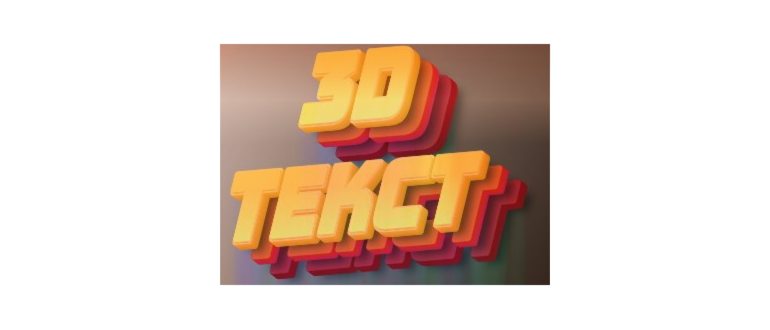
Клавиатура является основным инструментом работы на компьютере, и правильный выбор шрифта важен для создания красивого и удобного текста. Некоторые люди страдают от недостатка внимания к деталям и печатают безразлично. Однако, существуют методы, которые помогут вам создать красивый шрифт даже на обычной клавиатуре.
Первым способом является использование жирного шрифта. Жирный шрифт делает текст более выразительным и увеличивает его читаемость. Для создания жирного шрифта на клавиатуре, используйте комбинацию клавиш «Ctrl» + «B».
Второй способ — это курсив. Курсивный шрифт придает тексту эффект наклона и делает его мягче. Для создания курсивного шрифта на клавиатуре, используйте комбинацию клавиш «Ctrl» + «I».
Третий способ — это подчеркивание. Подчеркивание помогает выделить важные части текста и делает его более ярким. Для создания подчеркнутого шрифта на клавиатуре, используйте комбинацию клавиш «Ctrl» + «U».
Четвертым способом является выделение по контуру. Выделение по контуру добавляет тексту контур и делает его более заметным. Для создания выделения по контуру на клавиатуре, используйте комбинацию клавиш «Ctrl» + «Shift» + «O».
Пятый способ — это использование больших букв. Большие буквы привлекают внимание и делают текст более удобочитаемым. Для создания больших букв на клавиатуре, удерживайте клавишу «Caps Lock» включенной.
Шестой способ — это использование моноширинного шрифта. Моноширинный шрифт имеет одинаковую ширину для всех символов и делает текст более аккуратным и ровным. Для выбора моноширинного шрифта на клавиатуре, используйте комбинацию клавиш «Ctrl» + «Shift» + «M».
Седьмым способом является изменение размера шрифта. Увеличение или уменьшение размера шрифта может сделать текст более читаемым или добавить ему стильности. Для изменения размера шрифта на клавиатуре, используйте комбинацию клавиш «Ctrl» + «+» для увеличения или «Ctrl» + «-» для уменьшения.
7 способов создать красивый шрифт на клавиатуре
Создание красивого шрифта на клавиатуре может быть легким и интересным заданием. Ниже приведены семь способов, которые помогут вам создать стильный и оригинальный шрифт, используя только клавиатуру:
- Использование символов и специальных знаков. Некоторые клавиатурные символы могут быть использованы для создания интересных эффектов. Например, вы можете использовать символы, такие как «*»,»_»,»=» и другие, чтобы добавить украшение к вашему шрифту.
- Изменение размера шрифта. Вы можете изменить размер шрифта, используя клавишу «Ctrl» и «+»/»-» для увеличения или уменьшения размера шрифта соответственно. Это может помочь вам создать различные варианты шрифта с разными размерами текста.
- Использование различных шрифтов и стилей. Существует большое разнообразие шрифтов и стилей, доступных на клавиатуре. Вы можете использовать разные комбинации шрифтов, таких как «Arial», «Times New Roman», «Courier New» и других, чтобы создать уникальный шрифт.
- Применение эффектов форматирования. Вы можете использовать различные эффекты форматирования, такие как жирный, курсив, подчеркивание, чтобы выделить ваш текст и сделать его более привлекательным.
- Использование цветовых схем. Вы можете изменить цвет текста, используя комбинацию клавиш «Ctrl» и «K» для открытия палитры цветов. Выберите цвет, который наиболее подходит для вашего шрифта, чтобы сделать его более ярким и привлекательным.
- Изменение выравнивания и отступов. Вы можете изменить выравнивание и отступы вашего текста, чтобы создать уникальный и эстетически приятный шрифт.
- Использование таблицы. Вы можете использовать таблицу для создания структурированного и организованного шрифта. Разделите ваш текст на ячейки таблицы и установите различные стили для каждой ячейки.
Использование этих семи способов поможет вам создать красивый и стильный шрифт на клавиатуре. Экспериментируйте с разными комбинациями и стилями, чтобы найти наиболее подходящий для вас результат.
Используйте специальные символы и символы Unicode
Для создания красивого шрифта на клавиатуре можно использовать специальные символы и символы Unicode. Они помогут разнообразить текст, добавить оригинальность и привлечь внимание читателей.
1. Специальные символы:
- • Создайте ненумерованный список, добавив символ «мишень» – • – перед элементом списка.
- ◦ Отметьте пункты нумерованного списка с помощью символа «белый круг с точкой» – ◦.
2. Символы Unicode:
Используйте символы Unicode для добавления различных символов и декоративных элементов в свой текст. Ниже приведены примеры некоторых символов:
- ➡ Добавьте стрелку вправо, используя символ Unicode – ➡.
- ✔ Вставьте символ проверки, обратившись к коду Unicode – ✔.
- ❤ Для символа сердца воспользуйтесь кодом Unicode – ❤.
3. Символы для украшения текста:
Воспользуйтесь символами для украшения текста и добавления различных эффектов:
- ???? Для использования символа шрифта курсива используйте символ Unicode – ????.
- ???? Примените шрифт фракции к тексту, используя символ Unicode – ????.
| Символ | Описание |
|---|---|
| © | Символ «копирайт» |
| № | Символ «номер» |
| ≠ | Символ «не равно» |
Используйте эти специальные символы и символы Unicode в своем тексте, чтобы сделать его более интересным и привлекательным для чтения. Это отличный способ добавить оригинальность и индивидуальность в ваши сообщения и статьи.
Экспериментируйте с размером, шрифтом и выравниванием текста
Один из способов создать красивый шрифт на клавиатуре — это экспериментировать с размером, шрифтом и выравниванием текста. Варьируя эти параметры, вы можете создать уникальное оформление текста, которое подчеркнет его значение и привлечет внимание читателя.
Сначала рассмотрим размер шрифта. Вы можете выбрать мелкий размер шрифта для подзаголовков или небольших абзацев, чтобы создать более компактный вид. Более крупный шрифт может быть использован для заголовков или основного текста, чтобы сделать его более заметным и удобочитаемым.
Далее, выберите подходящий шрифт. Веб-браузеры предлагают множество стандартных шрифтов, но вы также можете использовать веб-шрифты или загрузить свой шрифт, если вам нужно что-то особенное. Помните, что шрифт должен быть четким и легко читаемым, даже при маленьком размере.
Не забудьте также использовать выравнивание текста, чтобы придать ему логическую структуру и сделать его более привлекательным для взгляда. Вы можете выровнять текст по левому, правому или центральному краю страницы, в зависимости от вашего предпочтения и дизайна страницы.
Использование разнообразных элементов форматирования текста таких как жирный () или курсив () может также сделать ваш текст более выразительным и захватывающим для читателя.
В заключение, экспериментируйте с размером, шрифтом и выравниванием текста на клавиатуре, чтобы создать красивый и привлекательный текст. Не бойтесь пробовать разные сочетания и находить свой уникальный стиль!
Используйте эффекты и стилизацию текста
Возможности стилизации текста на клавиатуре не ограничиваются обычным выбором шрифта. Вы можете добавить эффекты и стилизацию, чтобы сделать текст более выразительным и привлекательным.
Одним из основных способов стилизации текста является использование тегов и . Тег делает текст жирным, а тег — курсивным.
Также вы можете использовать теги
- ,
- для создания маркированных и нумерованных списков. Пример использования:
- Первый элемент списка
- Второй элемент списка
- Третий элемент списка
- Первый элемент нумерованного списка
- Второй элемент нумерованного списка
- Третий элемент нумерованного списка
Клавиатура также позволяет создавать таблицы с помощью тега
. Пример:
Заголовок 1 Заголовок 2 Заголовок 3 Ячейка 1 Ячейка 2 Ячейка 3 Ячейка 4 Ячейка 5 Ячейка 6 Используя эффекты и стилизацию текста на клавиатуре, вы можете создать красивые заголовки, акцентировать важные моменты и организовать информацию в таблицы и списки для более удобного чтения.
Используйте программы и онлайн-утилиты для создания собственных шрифтов
Когда стандартные шрифты уже надоели, можно создать свой собственный шрифт, который будет уникальным и отражать вашу индивидуальность. Сегодня существует множество программ и онлайн-утилит, которые помогут вам в этом деле. Вот несколько популярных вариантов:
- FontForge – это бесплатная и открытая программа, которая позволяет создавать и редактировать шрифты. Она поддерживает множество форматов, включая TrueType и OpenType, и предоставляет широкий набор инструментов для настройки каждого символа.
- Glyphs – это профессиональная программа для создания шрифтов, которая позволяет работать с множеством символов одновременно и автоматизировать процесс создания шрифта. Она платная, но предоставляет много возможностей для создания высококачественных шрифтов.
- FontStruct – это онлайн-утилита, которая позволяет создавать шрифты, используя графический интерфейс. Вам достаточно выбрать и настроить геометрические формы символов, чтобы создать свой уникальный шрифт.
- Calligraphr – это онлайн-утилита, которая помогает создавать шрифты на основе вашего почерка. Просто запишите буквы и цифры на бумаге, отсканируйте их и загрузите в Calligraphr. Затем вам нужно будет настроить каждый символ и сохранить готовый шрифт.
Не важно, какую программу или утилиту вы выберете, важно провести достаточное количество времени, чтобы создать шрифт, который полностью удовлетворяет вашим требованиям и ожиданиям. Выберите подходящий инструмент и начните создавать свой уникальный шрифт уже сегодня!
ПРОФИ отвечают на вопросы онлайн
Как создать красивый шрифт на клавиатуре?Существует несколько способов создания красивого шрифта на клавиатуре. Один из них — использование специальных символов и символов юникода. Также вы можете использовать различные эффекты форматирования, такие как жирный, курсив, подчеркнутый и зачеркнутый текст. Кроме того, стоит обратить внимание на размер и цвет шрифта, чтобы он соответствовал дизайну вашего текста или документа.Что такое символы юникода?Символы юникода — это специальные символы, которые не входят в обычный набор символов на клавиатуре. Они представляют собой стрелки, звездочки, сердечки и другие украшения, которые можно использовать для создания красивого шрифта. Чтобы использовать символы юникода, вам нужно знать их коды и ввести их с помощью клавиш комбинаций или специальных программ.Какие эффекты форматирования можно использовать для создания красивого шрифта?Для создания красивого шрифта вы можете использовать различные эффекты форматирования, такие как жирный, курсив, подчеркнутый и зачеркнутый текст. Каждый из этих эффектов придает вашему тексту особую эстетическую привлекательность. Они могут быть использованы как самостоятельно, так и в комбинации друг с другом для создания уникальных визуальных эффектов.Как выбрать правильный размер и цвет шрифта для создания красивого текста?Выбор размера и цвета шрифта зависит от ваших предпочтений и требований дизайна. Лучше выбрать размер шрифта, который является удобным для чтения и соответствует общей композиции текста. Цвет шрифта должен быть хорошо читаемым на фоне, на котором он будет использоваться. Идеальное сочетание размера и цвета шрифта создаст красивый и гармоничный текст.С помощью сторонних программ
- Установите программу с помощью «Плей Маркета». Запустите её, откройте вкладку «Мой». Щёлкните по настройкам.
Посмотрите, как выглядит новый стиль шрифта в системе и приложениях
Если в настройках устройства вы не нашли штатного инструмента для смены шрифта, вам нужно скачать и установить стороннюю утилиту с «Плей Маркета», например, iFont. Перед этим вам нужно установить в телефоне права «Рут», то есть получить права администратора смартфона, с которыми можно менять тонкие параметры системы. Для этого можно взять программу KingoRoot.
Опубликовано в Интересное
Как Сделать Красивый Шрифт на КлавиатуреСвободно переключаться на другие предустановленные в систему шрифты могут владельцы телефонов Samsung. Для этого:10 комментариевЮзабельна для меня только fonttextup.com полноценный конструктор надписей можно добавлять всякие эффекты шрифтаму меня в закладках 3 сайта — где я могу сгенерировать + скопировать и вставить сразу хуть на YouTube или еще куда. без всяких HTML, и всяких ⛎.
При использовании материалов с sdelaicomp.ru обязательным условием является использование ссылки на сайт
Мы более релевантной рекламы
Пользуясь сайтом, Вы автоматически принимаете «Пользовательское соглашение», а также правила передачи и обработки персональных данных, описанные в «Политике конфиденциальности»
Это абсолютно нормально для некоторых символов появляться в виде квадратов.
Хотите добавить свои собственные творения или не можете что-то найти? Отправьте нам сообщение! KонтактWhatsApp
В приложении WhatsApp очень ограниченные настройки шрифтов. Выбрать начертание, к сожалению, нельзя, доступно лишь изменение размера.
Особенность мессенджера WhatsApp в том, что вы можете форматировать текст в диалогах.
В Ватсапп доступно четыре стиля написания, которые используют для выделения важных мест в сообщении или повышения точности передачи информации.
- Чтобы написать текст жирным шрифтом, оберните его знаком * с двух сторон. Например, *CompConfig*. После отправки сообщения текст между звёздочками станет жирным.
- Для добавления курсива оберните слово или фразу нижним подчёркиванием _. Например, _Читайте нас_. Важно, чтобы перед первым нижним подчёркиваением и после второго был пробел. Форматирование применяется после отправки сообщения.
- Для создания зачёркнутого текста используйте знак тильды ~. Принцип аналогичный — оборачиваете слово или фразу с двух сторон и отправляете сообщение.
Ещё одна возможность — добавление в чат моноширинного начертания, которым часто пользуются разработчики. В WhatsApp доступен шрифт FixedSys. Чтобы применить его к тексту, оберните фрагмент в обратные одинарные кавычки. Вот так: «` Почувствуй себя разработчиком«` .
В системных настройках телефона
У вас на телефоне может быть встроенная возможность изменять шрифт. Но вероятность, что вам повезёт, мала: на большинстве телефонов штатный инструмент отсутствует. Обычно это он предоставляется на телефонах определённых производителей, например, в «Самсунге».
- Раскройте меню с настройками телефона. Щёлкните по блоку «Дисплей».
На любом устройстве вы сможете изменить только размер текста, но не его стиль. Для этого зайдите в раздел «Экран» в настройках, выберите пункт «Размер шрифта» и кликните по нужному варианту.
Мы более релевантной рекламы
Instagram
Instagram будет показывать надпись в том виде, в котором вы её вставили. Это отличная возможность для создания привлекающих внимание подписей и придания стиля вашему аккаунту.
«Выставите для нового файла Roboto-Regular.ttf права доступа как на скриншоте и сохраните изменения».
Хоть бы пол намёка на то, как это сделать. Где искать эти свойства и выставлять галочки?Какое именно приложение Theme Galaxy? Скачала что самое первое в поиске, а там нету второй инконки «Темы» что делать?
Дизайн и функционал приложений может меняться от версии к версии. Если в этом приложении нет нужной вам функции, попробуйте другое: https://www.samsung.com/ru/apps/galaxy-themes/
Увы, на Андр.11 через файл. -менеджер этот «танец с бубном» не работает. Скриншот на изображении не соотв. действительности (совсем другое изображение и окна для галочек ), не сохраняются изменения, а соответственно и шрифт
Шрифт с ярким стикер эффектом Редактировать Создать яркую стикер надпись
Как изменить шрифт в WhatsApp
Изначально в популярном мессенджере WhatsApp можно поменять размер шрифта для текстовых сообщений. Для этого после запуска программы открываем «Настройки» (три точки в правом верхнем углу), переходим в пункт «Чаты» и выбираем там «Размер шрифта». Предложено всего 3 варианта, по умолчанию стоит средний. Выбираем понравившийся, изменения сохраняются автоматически.
Есть еще несколько секретов написания текста в приложении, о которых не все знают.
Для того, чтобы выделить часть текста жирным шрифтом, нужно перед и после желаемого отрезка поставить знаки * (например «Нужно прийти *ровно* в 5 вечера!») После этого слово в «звездочках» становится выделенным жирным.
Для того, чтоб выделить что-то курсивом, нужно поместить это в нижнее подчеркивание (_пример_). Для зачеркнутого текста аналогично используем знак волнистого тире, а для написания в стиле разработчиков – поместить текст в 3 одинарные кавычки с обеих сторон (‘’’п р и м е р’’’).
Картины из текста и символов ୭̥⋆*。Текст искусство, также называемый ASCII искусство, образы создаются из текста. Например, вы можете использовать их в своих сообщениях на Facebook или в блоге!Как Сделать Красивый Шрифт на КлавиатуреК сожалению, на большинстве устройств встроенные возможности работы со шрифтами ограничиваются изменением размера. Однако некоторые производители встраивают в фирменные оболочки более гибкие инструменты.Можно ли написать название группы ВКонтакте нестандартным шрифтом?
Можно — но такая возможность предоставляется один раз и только для определенных шрифтов, в старой группе такое сделать с большой вероятностью не получиться, единственное что ВКонтакте пропустит без проблем — это, а нужен ли он вам? Лучше оставьте стандартный шрифт, чтобы не усложнять поиск группы.
Все права защищены. Использование материалов разрешено только с использованием прямой ссылки на сайт iq-you.ru
В настройках телефона
Для начала рассмотрим самый простой и доступный способ – это поменять написание в настройках вашего телефона.
Также возможность поменять качественные настройки шрифтов зависит и от модели телефона. Так, например, пользователи некоторых моделей Samsung, LG и HTC могут без особых усилий выбрать другой стиль написания прямо в настройках телефона. Для прочих же пользователей Андроида выбор остается только за размером текста.
Textfx.co – удобный сетевой генератор текстов
И последний сервис, о котором я хочу поведать – это textfx.co . Он также имеет англоязычный интерфейс и большое разнообразие шрифтов, а работа с ним не отличается от других ресурсов данного плана. При этом свободный доступ к ресурсу ограничен выполнением двух надписей в день (за большее количество придётся доплачивать).
Способ 2: Параметры лаунчера
Этот метод наиболее близкий к системным настройкам и заключается в использовании встроенных инструментов любой установленной оболочки. Расписывать процедуру изменения мы будем на примере только одного лаунчера «Go», в то время как на других процедура отличается несущественно.